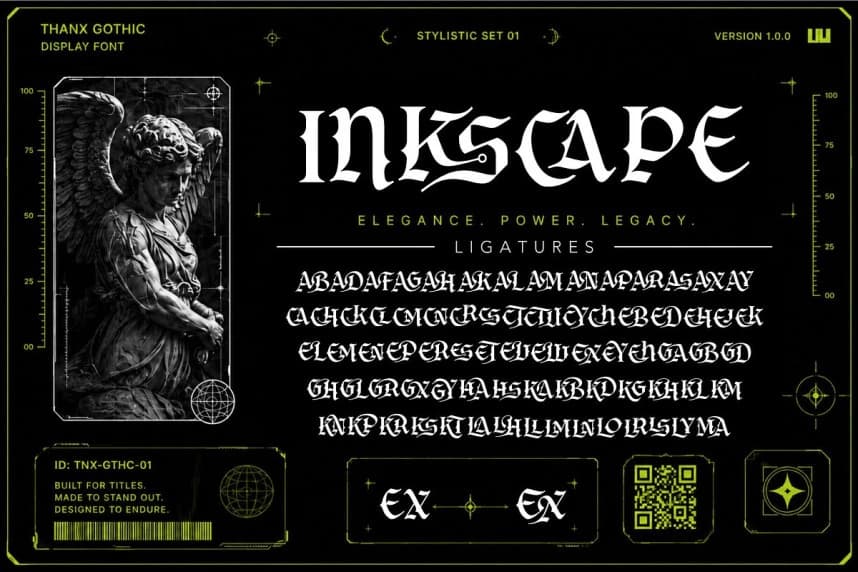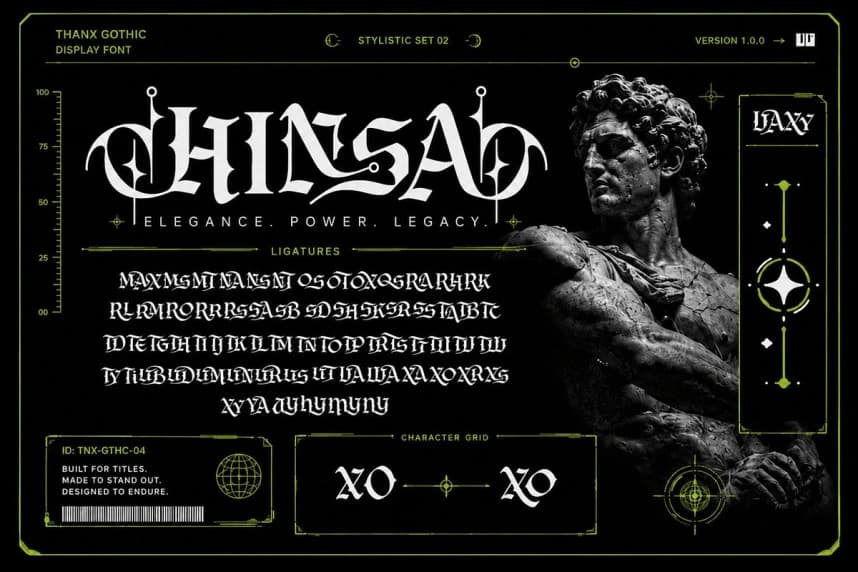
Dark Hermes Yazı Tipi
Dark Hermes Font. Klasik miras şekillerinden ilham alan ve modern, keskin bir dokunuşla birleşen bu yazı tipi, keskin zarafet ile güçlü otorite arasında mükemmel bir denge kurar.
Dark Hermes Font. Klasik miras şekillerinden ilham alan, modern ve keskin bir dokunuşla harmanlanmış bu yazı tipi, keskin zarafet ile güçlü otorite arasında mükemmel bir denge kuruyor.